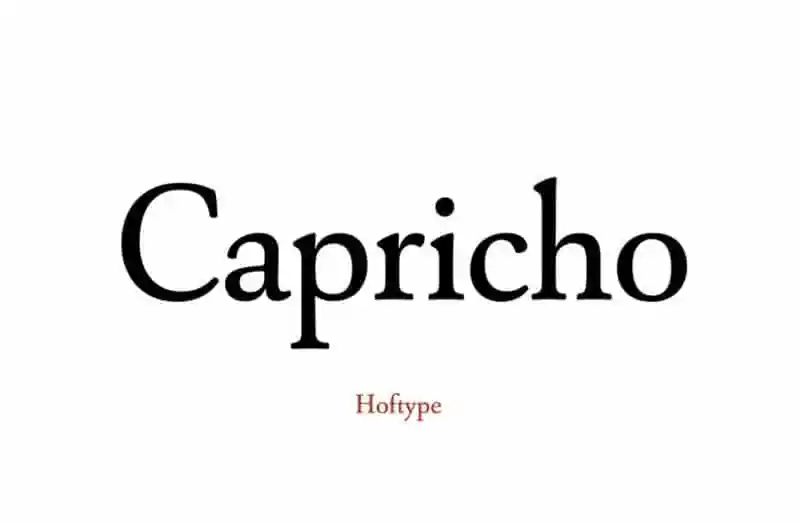
A Capricho Serif Font é uma elegante tipografia serifada criada pelo Hoftype. Embora tenha suas linhas retas definidas pela natureza das serifas, a Capricho possui borduras suaves e formas que fluem naturalmente, oferecendo um toque suave aos seus gestos de escrita. Esta fonte mistura os atributos de uma tipografia transitional do século XVII, com sua própria personalidade única e distintiva. Ideal para ambientes que exigem uma aparência sofisticada e profissional, a Capricho é perfeita para textos legíveis e impecavelmente formados. Seja em um projeto editorial complexo ou simplesmente no layout de um documento, a Capricho será o complemento perfeito, oferecendo um visual sólido e sofisticado.